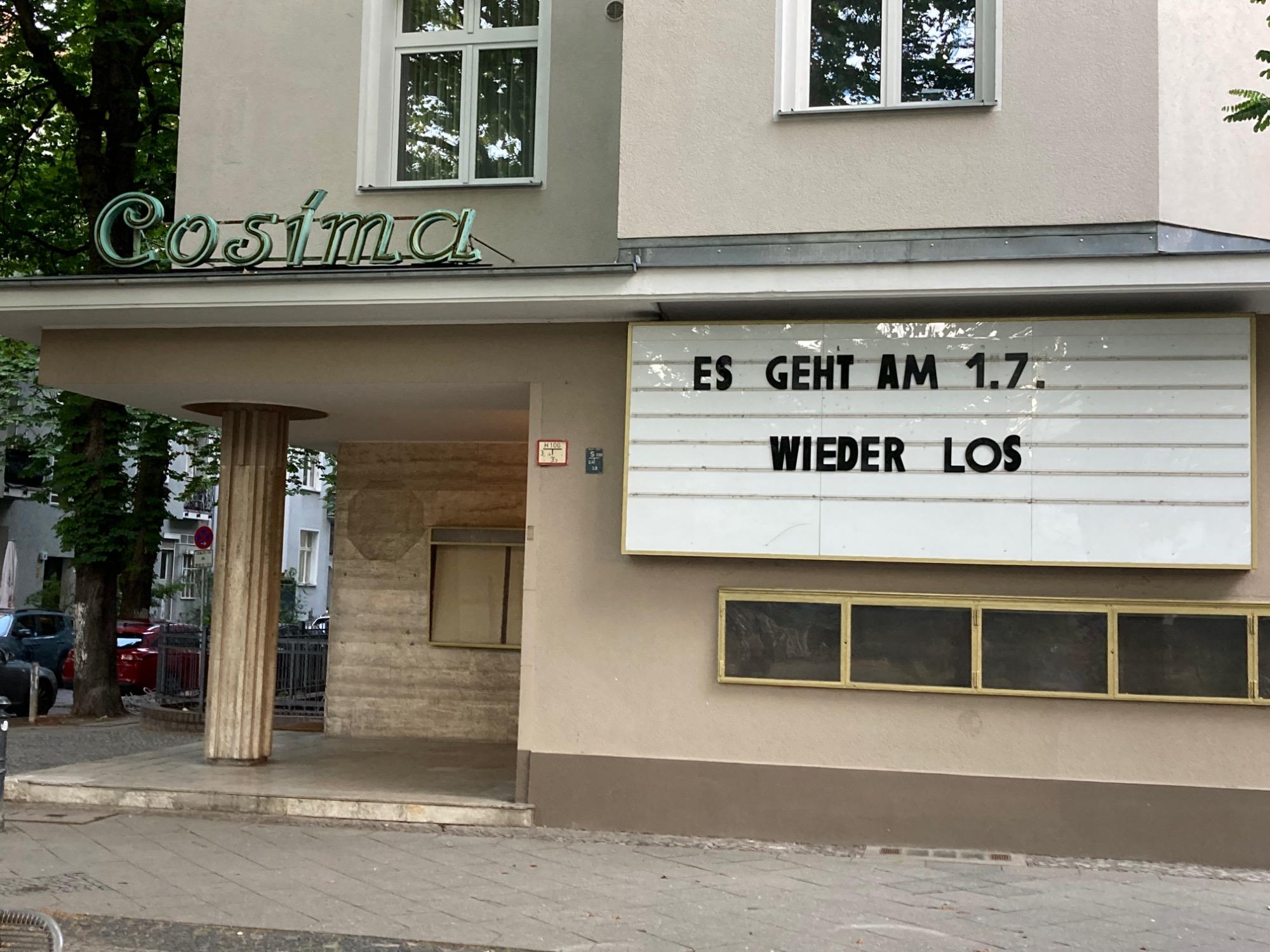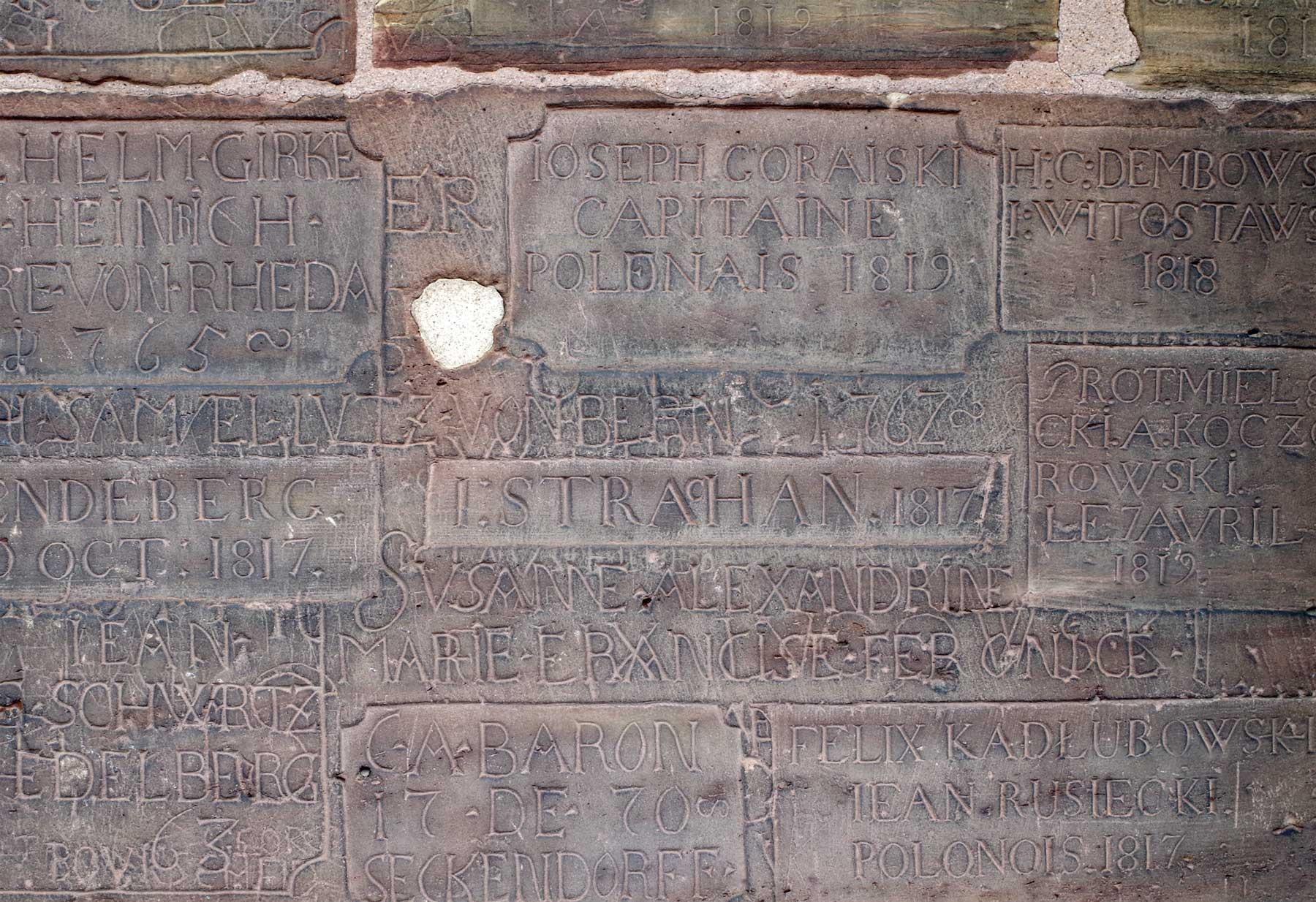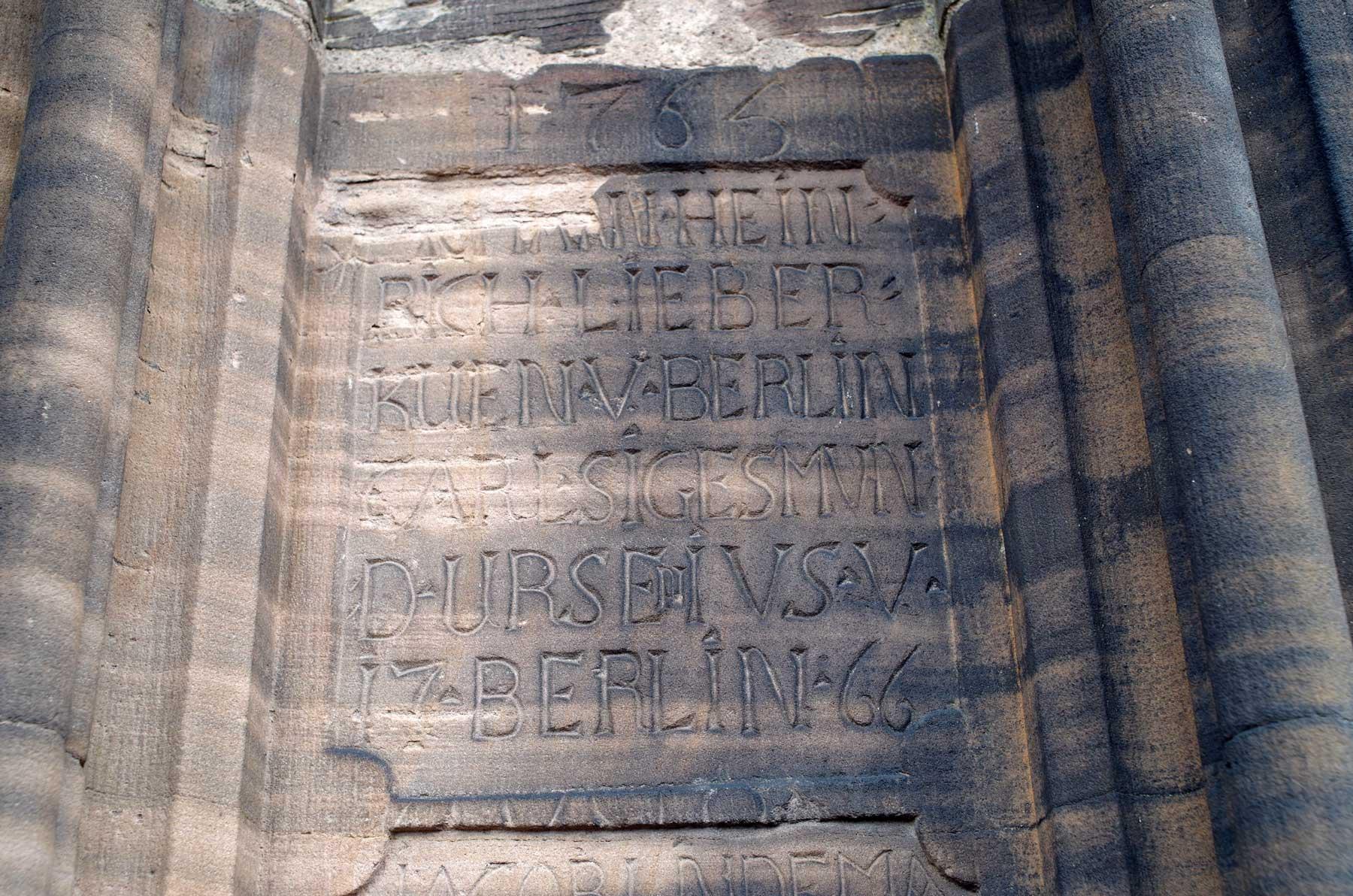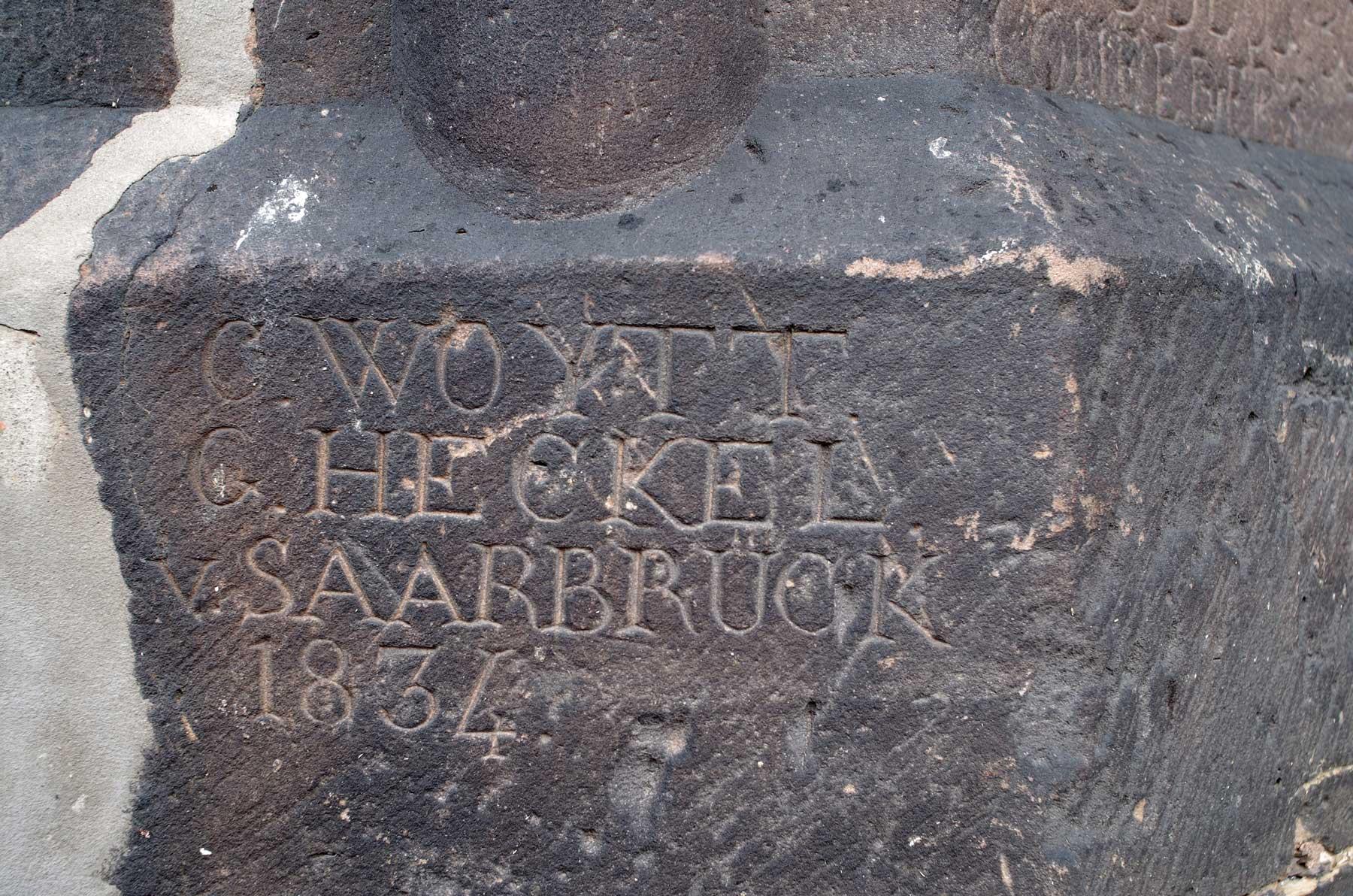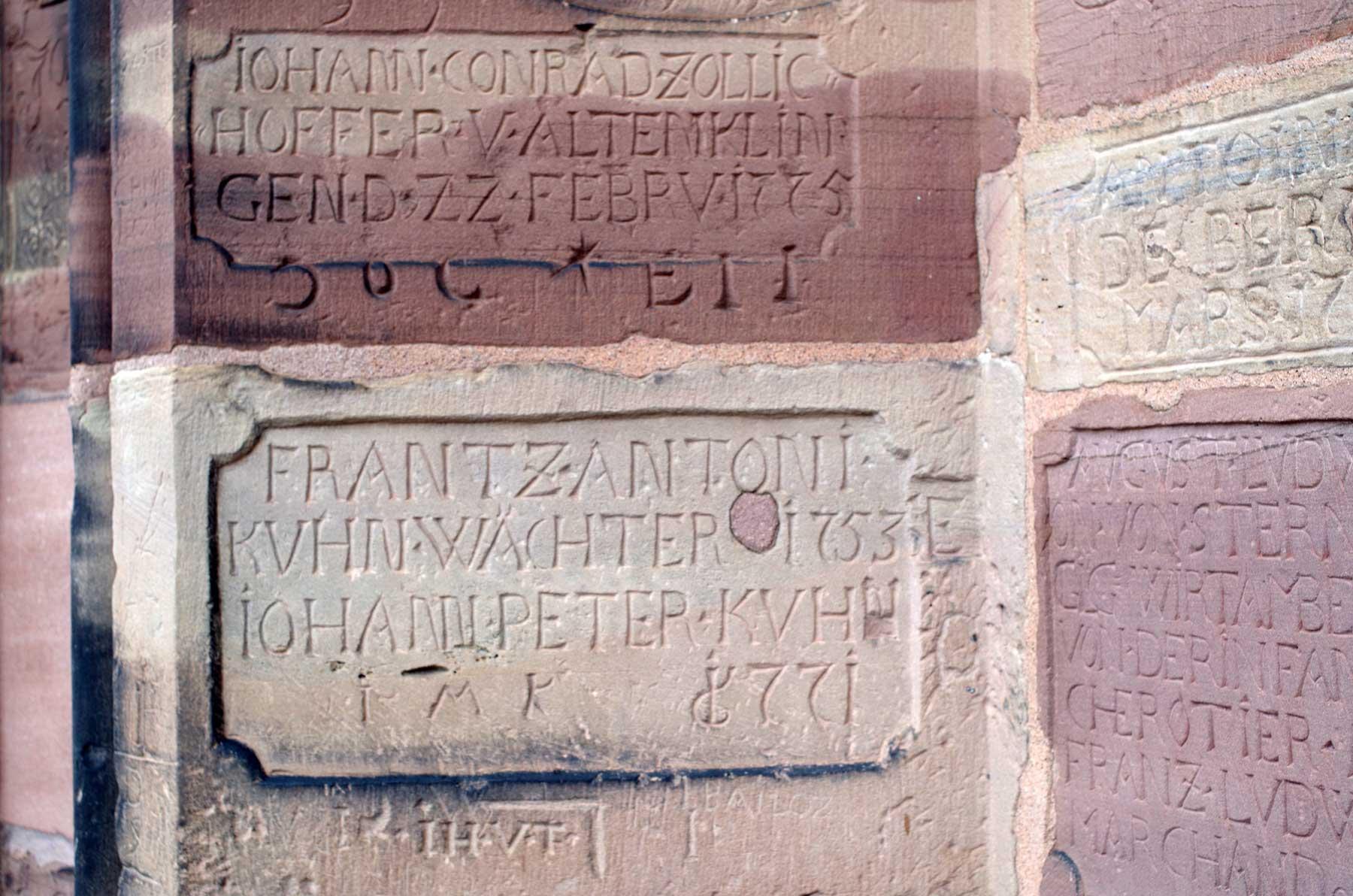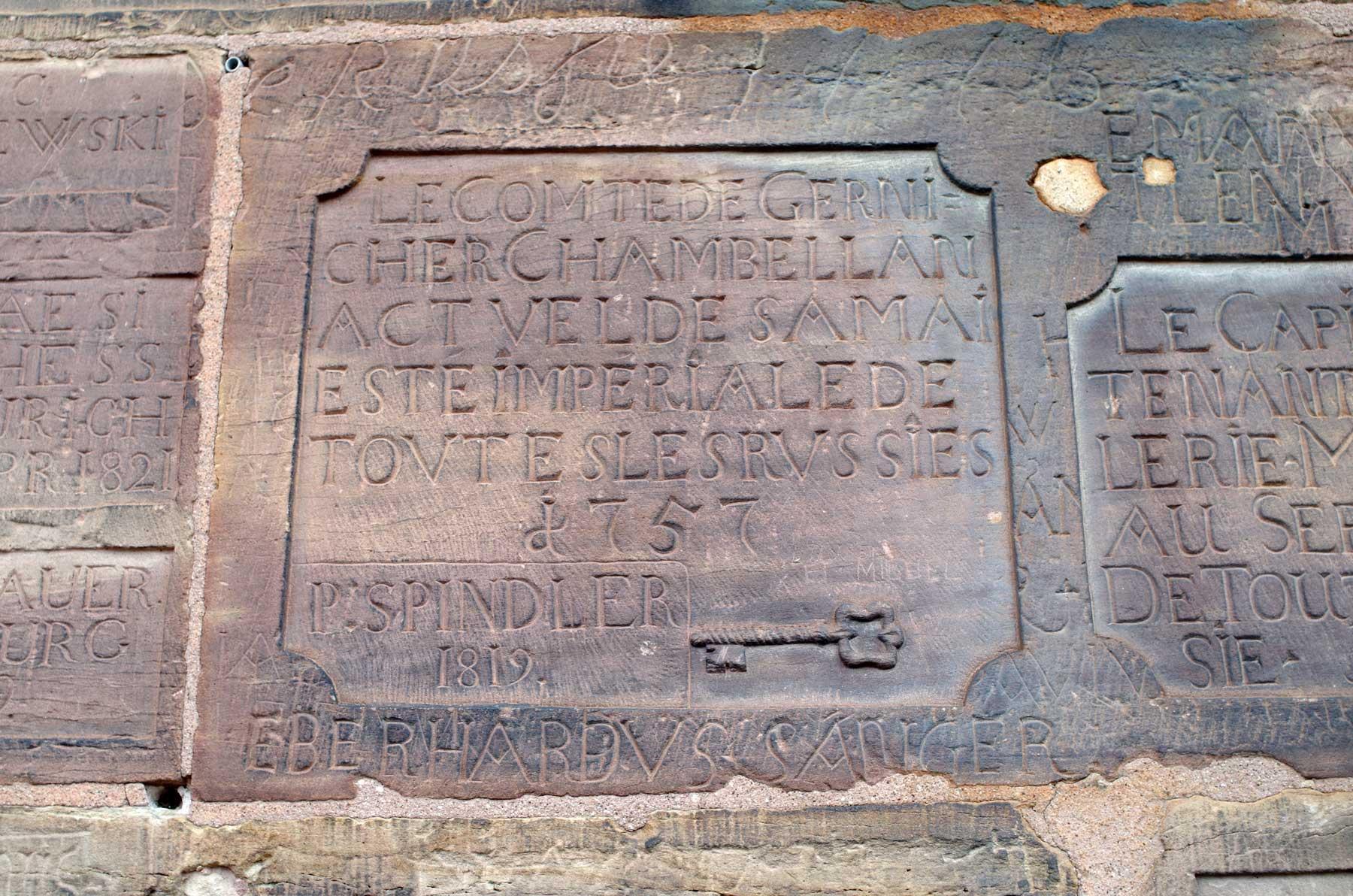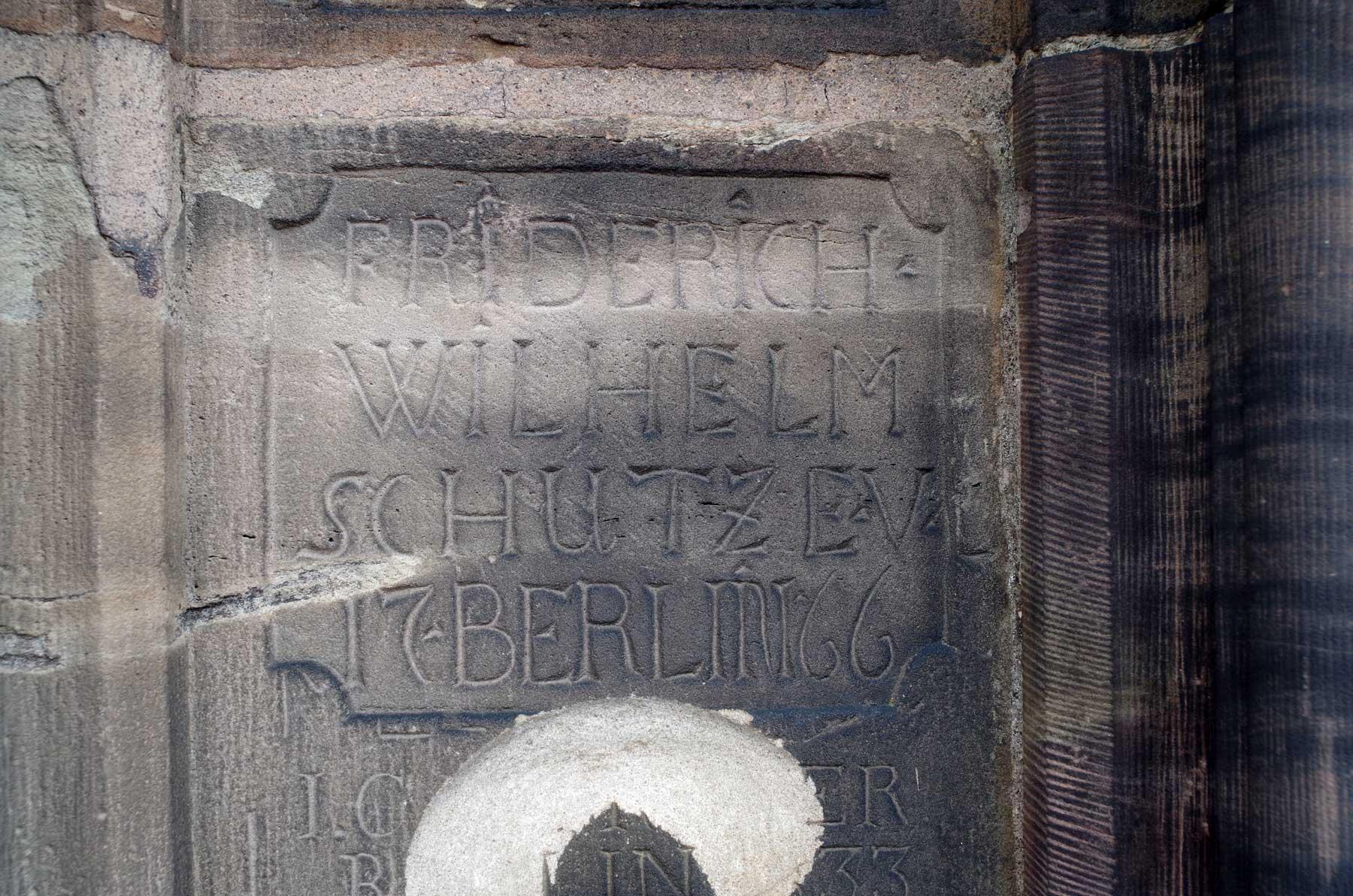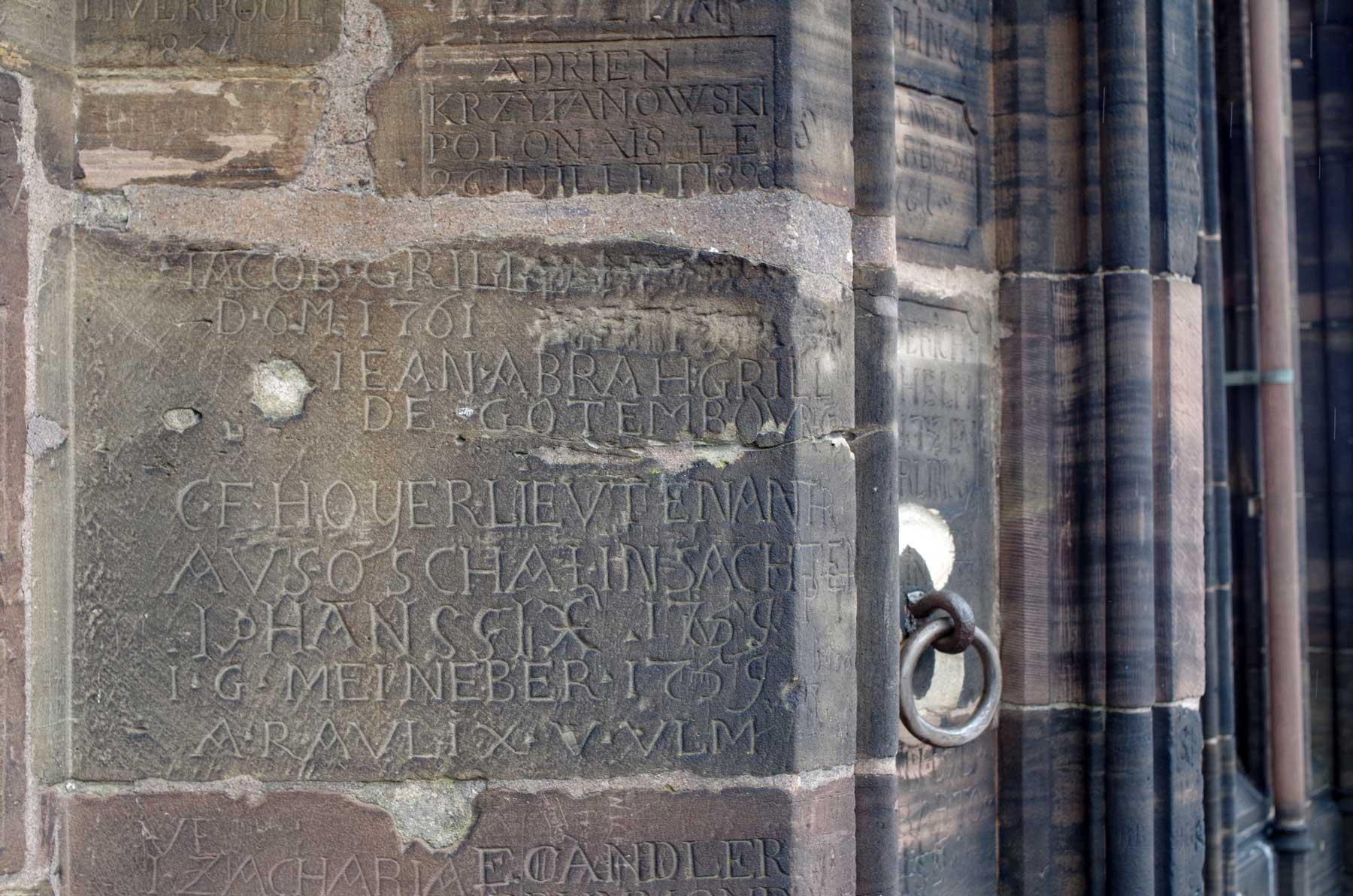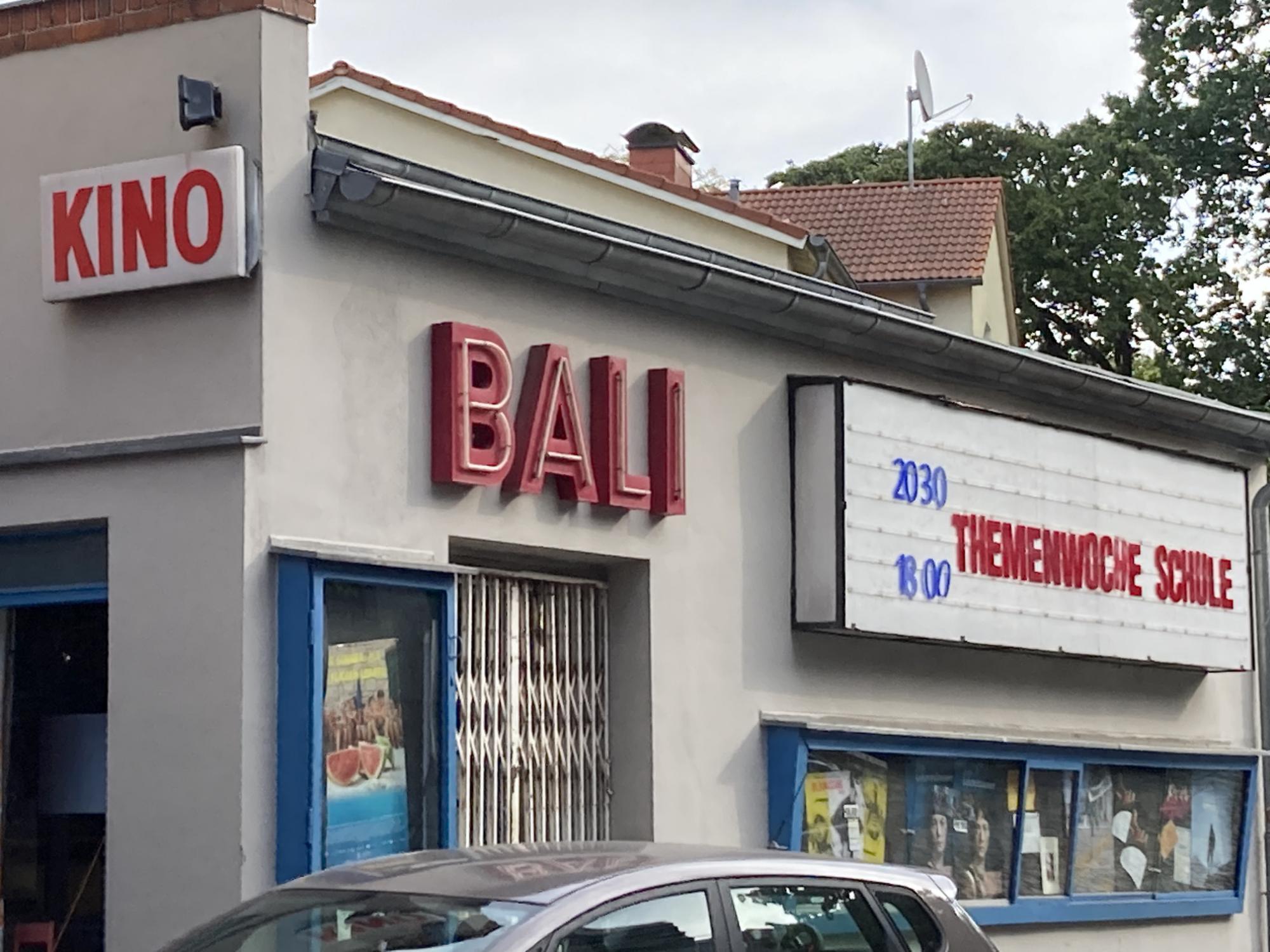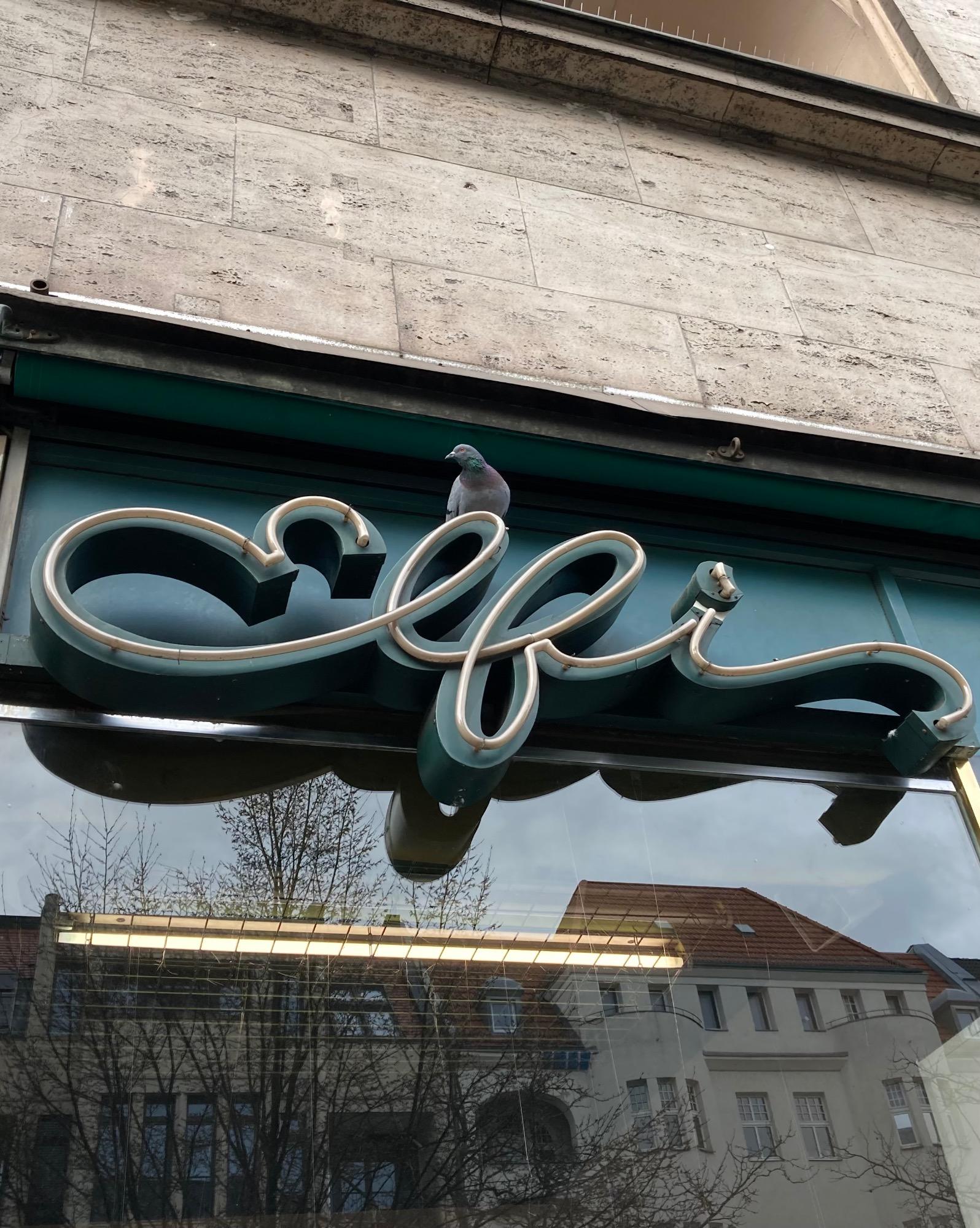
Typostreifzug durch die Stadt ...
Danke für die Aufklärung. Ich finde die Schrift als Auszeichnungsschrift auf dem Spielplan anstrengend zu lesen, aber trotzdem finde ich sie irgendwie zu der jugendlichen Ecke eines Traditionshauses passend.
… und frage mich jedes Mal auf's Neue, ob es ein Versal-Eszett ist oder nicht. …
Doppelt falsch: 1. kein Versal; 2. auf das kleine s bezogen, der klassische Tschichold-Fehler.
Da ist mir ein besoffenes großes O lieber.
Sind nicht die frühen Vorkommen wie z. B. in der Schelter Antiqua 24 auch auf Kleinbuchstaben bezogen, in dem Fall ſ und z?
Wenn Tschichold die Herkunft des ß aus ſ und s schließt, ist das sicherlich nicht ganz richtig. Aber das macht die Gestaltung ja nicht falsch. Das ist halt einfach eine Entwicklung …
Mal ein bewegter Streifzug 🙂
Aus einem technischen Werbefilm (was es nicht alles gibt/gab) von 1951 der Hochbahn -- die U-Bahn Hamburgs: image.png.bc5e8d01b7bce5431dffedd7dd1afebf.png
Es gibt nicht nur Aufnahmen eines kriegsgeschädigten, aber emsigen Hamburgs mit einiger Straßenbeschilderung (so hieß die Haltestelle noch Barmbeck), sondern auch noch en passant etwas zur Eisenbahnsignaltechnik:
Ich war am Wochenende mal ein bisschen Buchstaben sammeln … 🙂
Auf einer zehnminütigen Busfahrt kam ich an folgenden vier Schmuckstücken vorbei. Der wahre Typograph braucht eben (fast) nur eine Schrift … 😐
Handarbeit :wink:
Und das darf auch nicht fehlen:
Für den Futura-Fan:
Hübsch:
Faszinierend sind diese "vertikalen Ligaturen" auf dem Schild der Rasiererzentrale: AV, dann UI, genial DD welche vertikal wie ein krasses B auftreten, IE und dann noch OO welche zur 8 werden.
Da hat jemand Selbstvertrauen oder Klebebuchstaben in den Größen "brontal" und "brontal+". Und was mich selbst erstaunt: Mir gefällt dieses Schild. Handarbeit mit Inbrunst.
Daran komme ich in Barmbek regelmäßig vorbei und stolpere ebenfalls regelmäßig über die Frage, was "mitglied" wohl für ein Verb hätte werden sollen...
Ist das provozierende Absicht eines kreativen Kopfes oder hat da jemand einfach mal ne Powerpoint-Präsentation zum Drucker geschickt und die Folien nebeneinander drucken lassen?
… in virus times, ahem (gar so schlimm steht es nicht um die Berliner Kinolandschaft, scheint ein spezieller Fall zu sein. Kann mich noch an die Zeit erinnern, wo es da Borsalino & Co. zur Matinee gab)
Endlich mal eine gute Nachricht aus Berlin:
Pessimisten würden jetzt drauf hinweisen, dass die Angabe des Jahres fehlt.
Würde 23 nachgerüstet, würden sie "2123?" fragen.
Würde die 20 nachgerüstet, würden sie "nach Christus oder Allah?" fragen ...
Weiß nicht, wenn da jetzt noch eine Jahreszahl stünde, wär das kein so richtig optimistisches Statement, trotzdem freue mich jedenfalls dass es bis zum 1. 7. nicht mehr so lang hin ist :-)
PS: Und ein ausgeschriebener Monatsname hätte vielleicht noch mehr erfreut … die Ungewissheit hat mir aber jetzt keine Ruhe gelassen, und obwohl auf den üblichen Online-Kinoprogramm-Plätzen nichts zu finden war, spricht ein lokaler Blog von einer ersten regulären Vorstellung am 6. Juli:
Am 1. Juli sind  alle Interessierten zu einer kostenlosen Kino-Tour um 16, 18 und 20 Uhr eingeladen. Das reguläre Kinoprogramm startet am 6. Juli 2023 mit Alma & Oscar, ein Spielfilm von Dieter Berner mit Emily Cox als Alma Mahler und Valentin Postlmayr als Oskar Kokoschka.
Auf dem Blog gibt es noch etwas mehr Hintergrundinformationen und ausserdem noch etwas mehr visuelles Material für den (West)Berliner Kino-Nostalgiker … wunderschön.
Straßburger Münster, Aussichtsplattform, Mitbringsel aus dem Urlaub. Graffiti, die quasi als Nebenerwerb von den Turmwächtern für damalige Touristen erstellt wurden, auch ein paar Berliner dabei …
Urgestein der West-Berliner Kinolandschaft in Zehlendorf: Das Bali, zum letzten Mal vor Jahrzehnten für eine Tarkowski-Retro besucht (die noch in der Sowjetunion gedrehten Filme Tarkowskis sind mittlerweile alle online auf dem YouTube Kanal von Mosfilm frei verfügbar, darunter auch Der Spiegel mit der – Typo im Film! – eindrücklichen Sequenz in der die Tarkowskis Mutter, eine Korrektorin, personifizierende Darstellerin in Panik nach einem vermuteten Fehler in einer wichtigen Lenin(?)Ausgabe sucht, ab Minute 22:23)
Photo-Haus:
Das Logo von Fördern und Wohnen mit dem schönen Achterknoten-& erfährt auf der Website des Trägers in einem Video eine nette Einbindung: https://www.foerdernundwohnen.de/unternehmen/unternehmensprofil
Ich finde, mit dem Logo ist dem*r Designer*in ein echt großer Wurf gelungen.